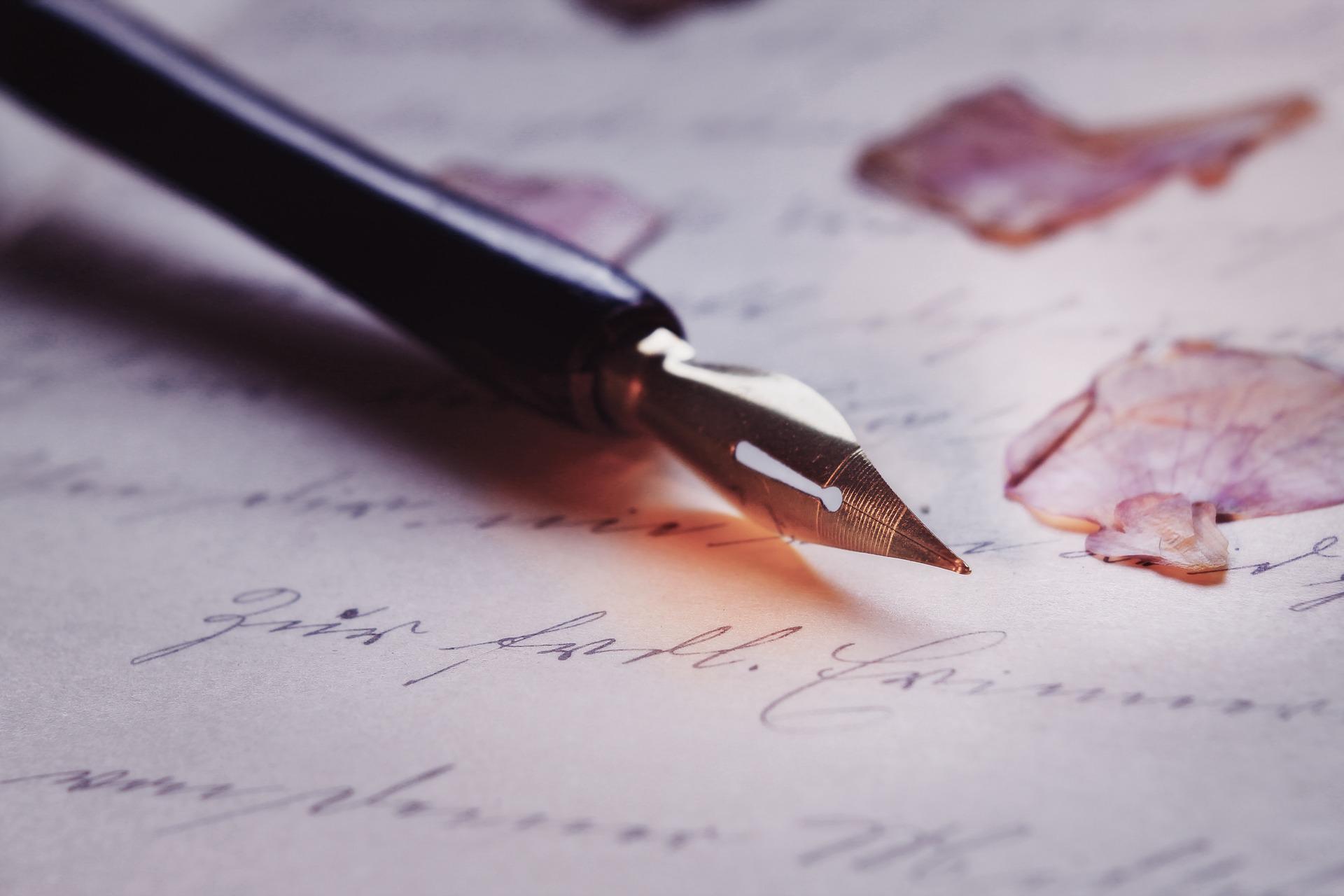
La bellezza della scrittura a mano è intramontabile. Nessun formato digitale e tecnologie innovative potranno mai eguagliare il piacere dello scrivere a mano. Così come sarà ineguagliabile la bellezza imperfetta della scrittura a mano. Tanto bella e ineguagliabile che si cerca di imitarla anche nei font. Scopriamo insieme cosa sono i font calligrafici e dove trovarli.
Cosa sono i font calligrafici
“Non so spiegarmi perché mi dia tanto piacere scrivere a mano, quasi che un foglio di carta e una buona penna mi compensassero dallo sforzo di pensare” – Roland Barthes.
I font calligrafici altro non sono che un tipo di font che imita la scrittura a mano. Sono per lo più in corsivo, caratterizzati da glifi e da uno stile elegante, dinamico, estroverso e divertente.
La calligrafia
I font calligrafici prendono il loro nome dall’arte della calligrafia. Con questo termine non si indica lo scrivere a mano, in modo generico, ma una tipologia di scrittura a mano più elegante, pulita e bella da vedere.
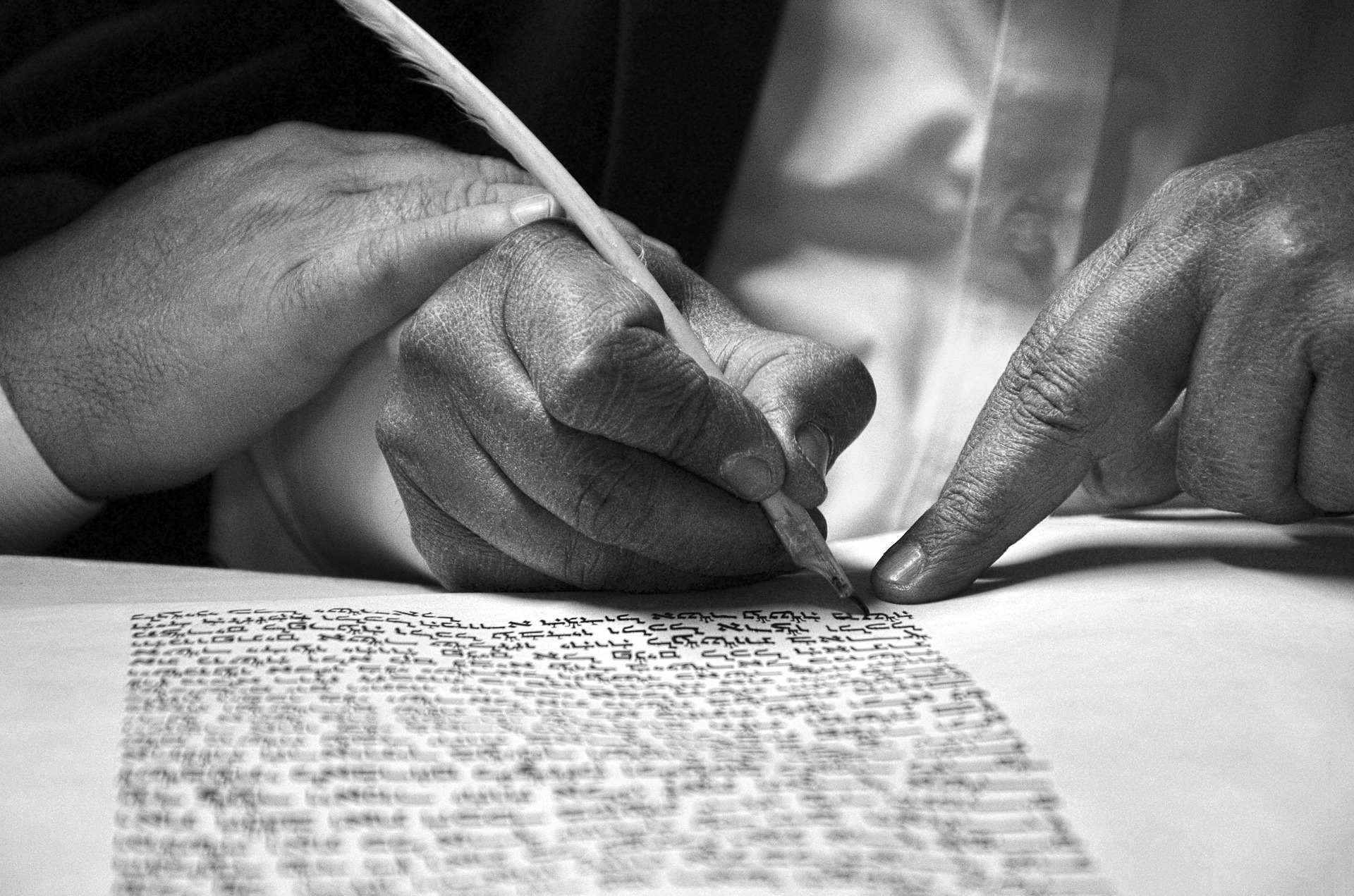
La calligrafia è una vera e propria forma d’arte. L’arte di scrivere con lo scopo di esprimere la bellezza delle parole e delle lettere stesse.
Nel campo, gli esperti “datano” la calligrafia a molto prima dell’inizio della scrittura stessa. Le pitture rupestre realizzate tra 25.000 e 30.000 anni fa, vengono anch’esse considerate una prima forma di calligrafia antica. Rientrano nella calligrafia antica anche i geroglifici egiziani (3500 a.C.) e i simboli dell’alfabeto fenicio (1000 a.C.)
Ma per la prima forma di calligrafia moderna, così come la intendiamo noi, dovremo attendere fino ai primi libri scritti in latino dagli scribi.
Siamo nel medioevo e ai monaci venne assegnato il compito di imprimere la parola di Dio sulla carta. Lo fecero donando “bellezza” alle lettere scritte a mano, utilizzando quello che noi conosciamo come stile Gotico.
La calligrafia divenne “di moda” nel quindicesimo secolo e una vera e propria forma d’arte nel Rinascimento.
Font calligrafici: scrittura classica o calligrafica
Ma torniamo a noi, perché nel mondo dei font vengono definiti calligrafici tutti quelli che imitano la scrittura a mano. Possiamo, tuttavia, distinguerli in due gruppi: quelli che si rifanno alla scrittura classica e quelli che imitano l’arte calligrafica.
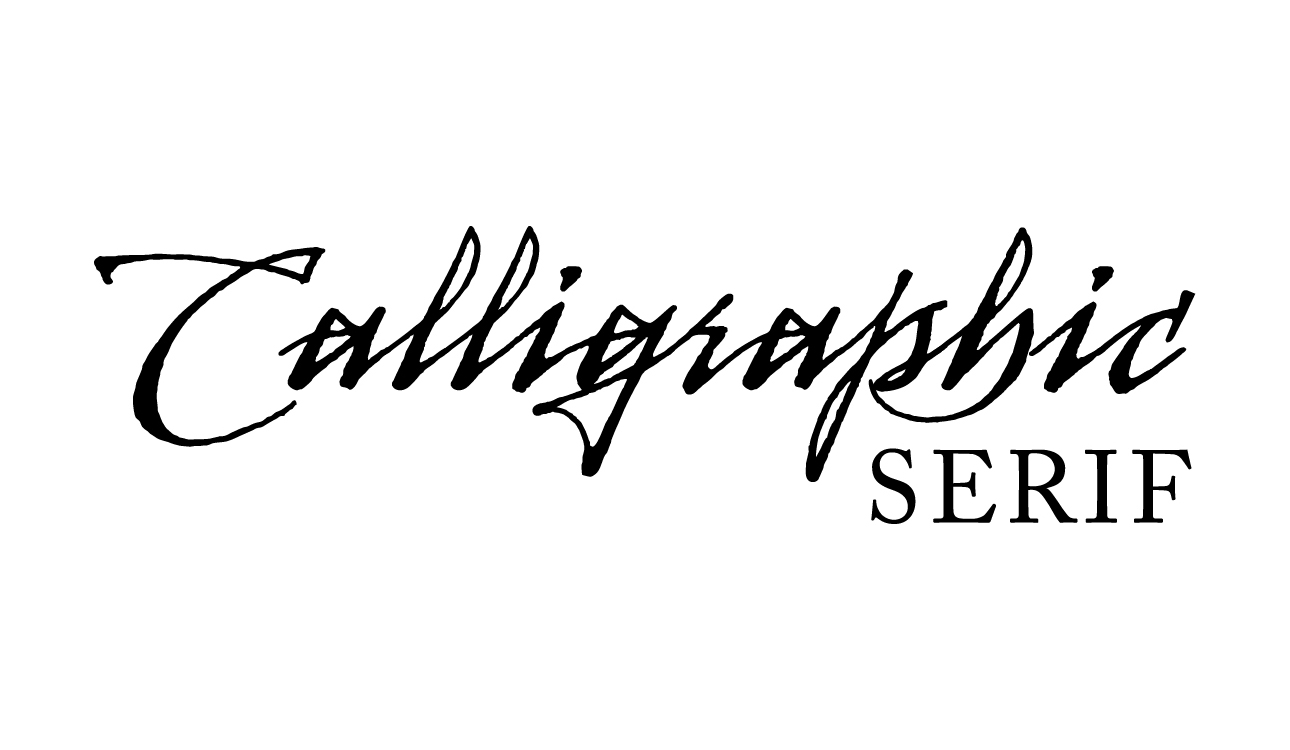
I primi imitano la scrittura manuale di tutti i giorni, quella che utilizziamo sovrappensiero, che usiamo per prendere appunti e che esprime la nostra personalità, le nostre abitudini e il nostro stile.
La seconda è, appunto, quella che imita l’arte della calligrafia. Si tratta, quindi, di una scrittura manuale ma, a differenza di quella di tutti i giorni, è più pulita, precisa, elegante e delicata.
Font calligrafici: quali sono?
Di font ne possiamo trovare davvero tantissimi, nei programmi di uso quotidiano o scaricabili dalle piattaforme, gratuiti o a pagamento.
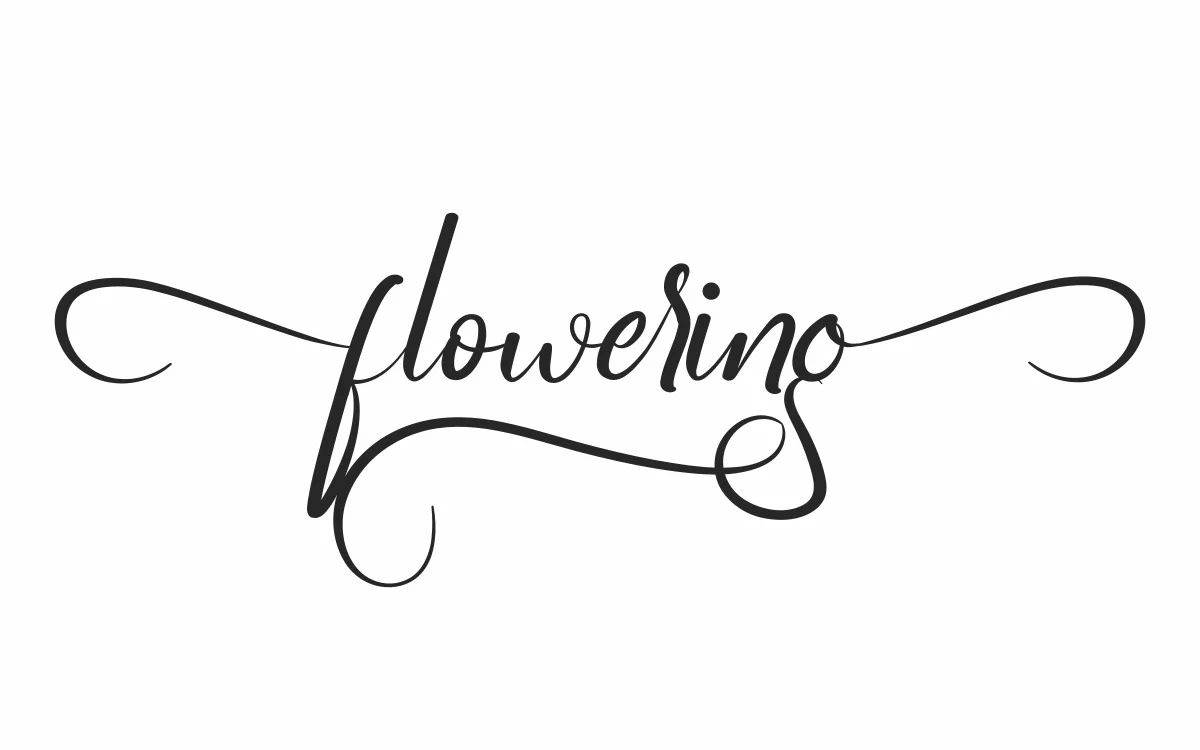
Ve ne sono moltissimi che rientrano nella categoria “calligrafici”. Essi sono apparsi per la prima volta intorno al 1500, per imitare la scrittura a mano. Alcuni sono ispirati a scrittori o personaggi storici e importanti, come il Jane Austen o il Dalì. Ce ne sono con stili “infantili” o “adulti”, caotici o eleganti.
Molti marchi famosi hanno scelto i font calligrafici per i loro loghi. Harrods, Barbie, Walt Disney, Pierre Cardin, Salvatore Ferragamo, Johnson’s, ecc.